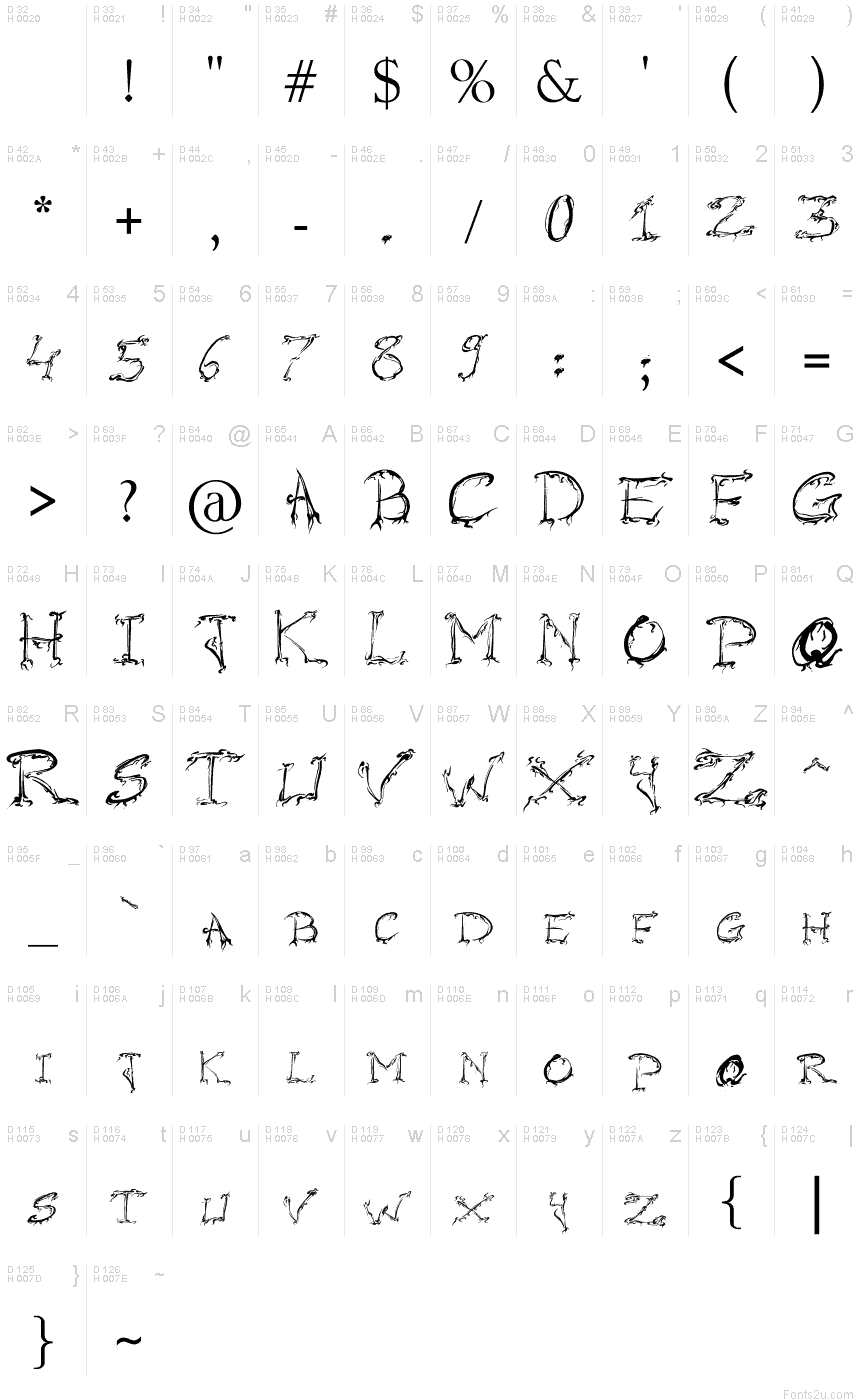
Raslani Horrorz, di le Raslani, è un font horror gratuito da titolo dal look grezzo, disegnato a mano. Le lettere sembrano tratte da vecchi poster horror pulp, con tratti sottili e filiformi, estremità ad uncino e curve irregolari che conferiscono al font un aspetto inquieto e quasi selvaggio.
Si presta naturalmente a poster horror, volantini per Halloween, branding di attrazioni infestate, copertine di fanzine e titoli crudi che necessitano di quell'atmosfera instabile e lacerata. Essendo un font gratuito, è ideale anche per nomi di band, incipit di capitoli o brevi titoli, poiché la silhouette spigolosa trasmette una forte atmosfera anche senza l'aggiunta di effetti extra.